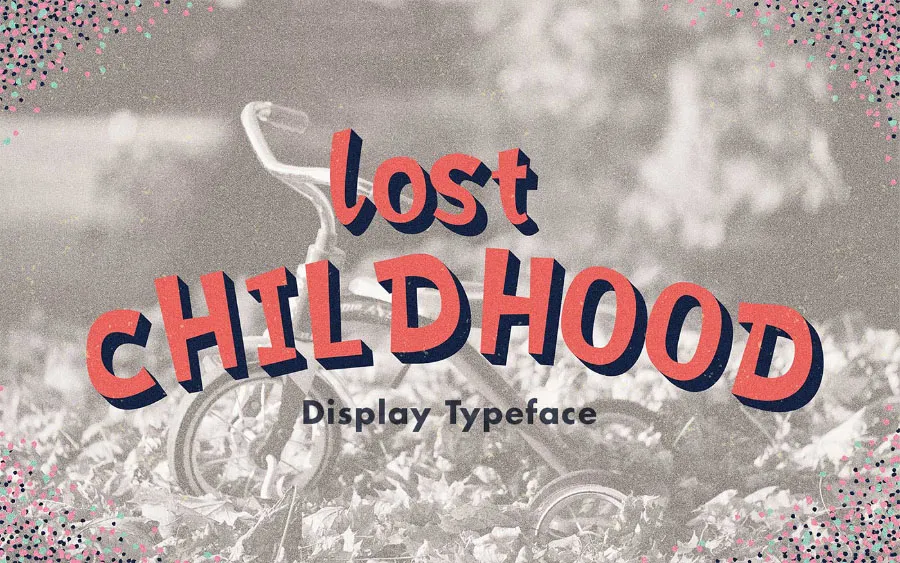
Lost Childhood Font – Fonte Grátis
Lost Childhood Font
Aqui está uma descrição em português para a página de download da fonte “Lost Childhood Font” dentro do formato solicitado: Glad to introduce to you a new display font designed by Oban.co, Lost Childhood Font! Este é um tipo de fontes modernas e bold, projetadas para complementar e dar vida aos estilos retro animados dos desenhos Flintstones ou Jetsons. Perfeita para ilustrações em roupas íntegras ou embalagens antigos, a fonte foi desenvolvida pensando nas ilustrações, o que a torna perfeitamente harmoniosa com essa estética única e vintage. A serenidade de Lost Childhood é perfeita para projetos de design que buscam uma combinação assertiva entre o moderno e o retrô. Ideal tanto para criações digitais quanto impressões em papel, esta fonte traz um toque especial a qualquer projeto de arte gráfica.